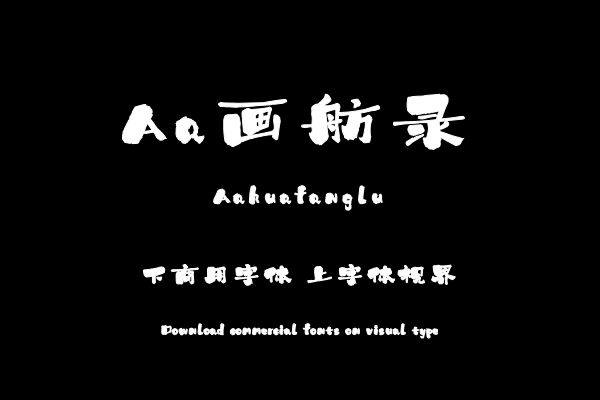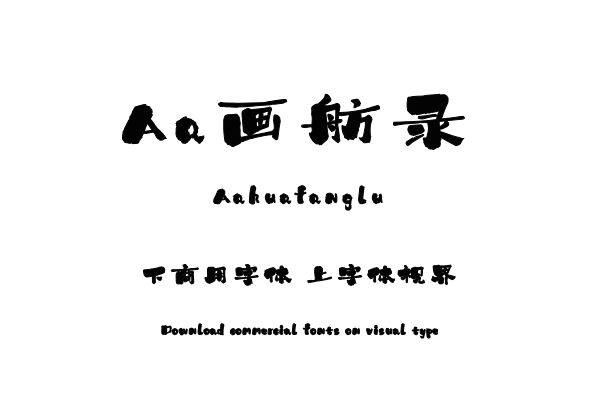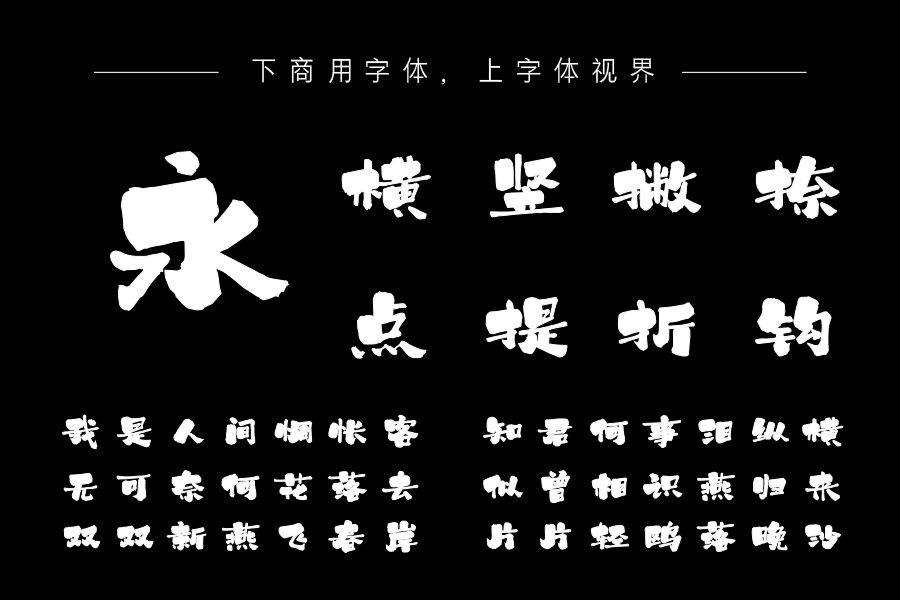
字体笔画特征为粗细强烈对比,横画细长而上扬,结合偏扁的结构,让整个字呈现飞翔上升的势头,粗笔画粗重膨胀,拙稚可爱,整个字粗细有致,动静相宜。购买须知:“下载服务费”与“字体VIP”所获得字体 仅用于个人非商用, 商用请联系付费授权。本字体为电脑用字,手机没有root权限不支持直接手机换字(手机如何root,请自行百度搜索教程)。购买前请先 了解清楚后再付款 ,字体为虚拟产品无法回收 一旦购买不支持退款。